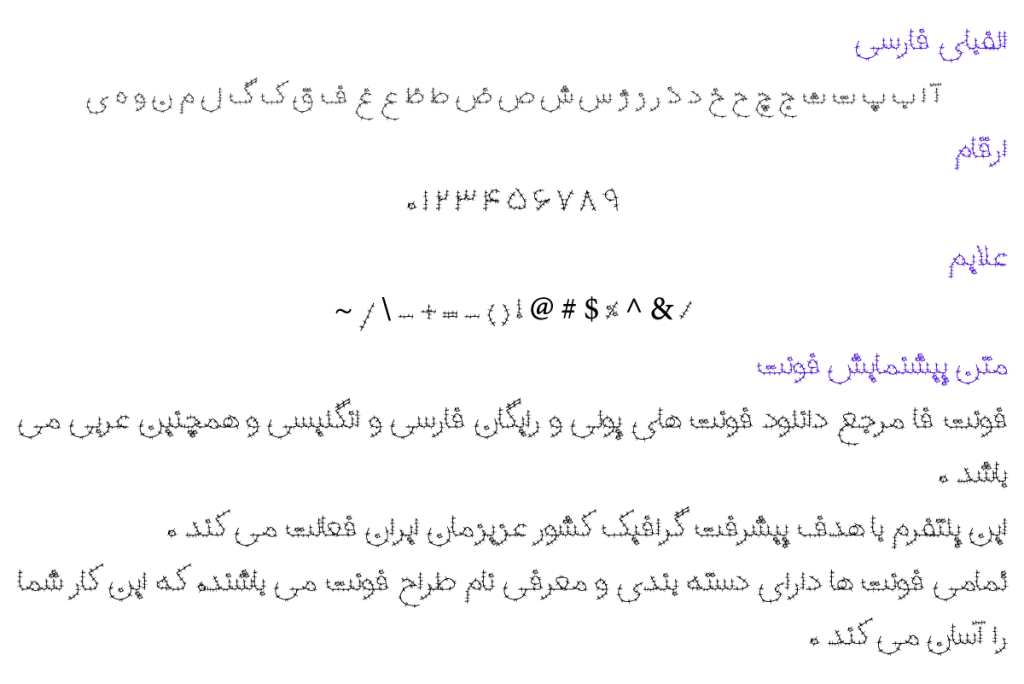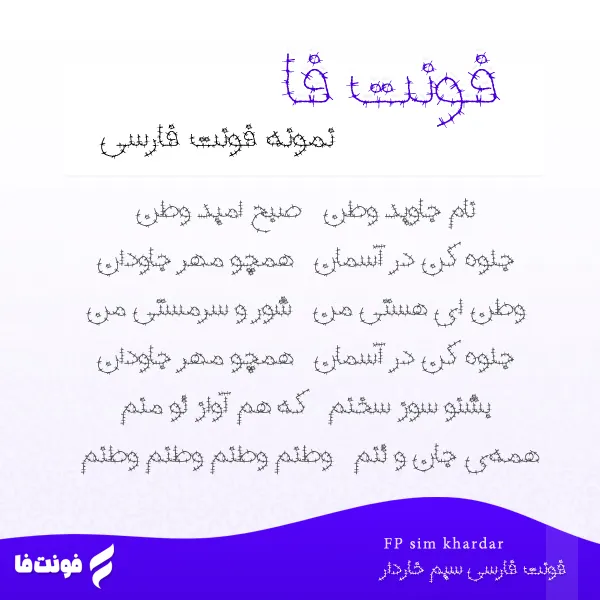
فونت فارسی سیم خاردار – FP sim khardar
سال ساخت فونت: 1392
طراح فونت: محمد عموئی نوع فونت: فونت فانتزی
پیشنمایش فونت سیم خاردار
توضیحات و معرفی فونت سیم خاردار
فونت فارسی سیم خاردار ( FP sim khardar ) از مجموعه فونت های آزاد می باشد، همینطور نوع فونت فانتزی می باشد.
فونت زیبای مرتبط توسط محمد عموئی در سال 1392 طراحی و ساخته شده است.
در تصویر زیر میتوانید شعر دلنشین «نام جاوید وطن» را ببینید که با این تایپ فیس فارسی طراحی شده است.